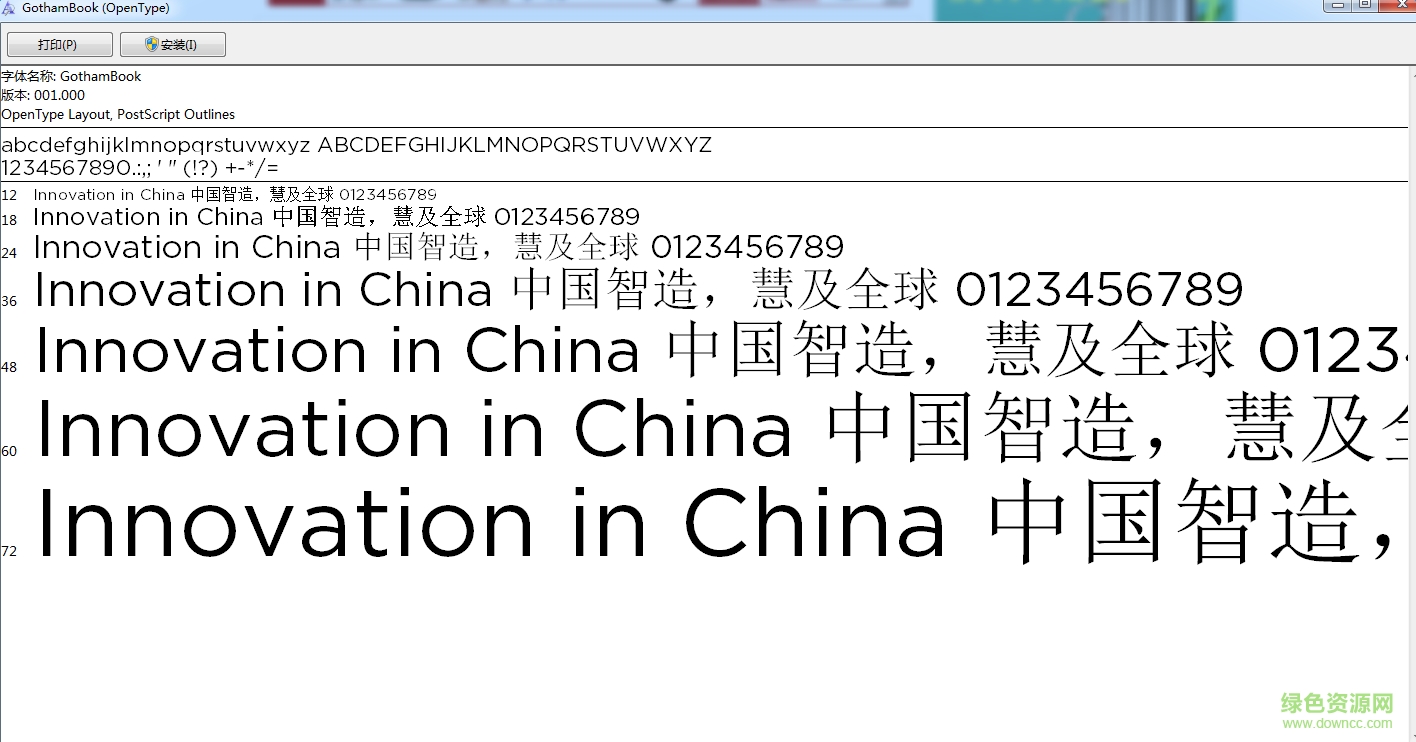
gotham book字體是一款制作精細(xì)的無(wú)襯線字體,結(jié)構(gòu)方正,規(guī)整劃一,現(xiàn)代感十足,可用于雜志、報(bào)刊的正文字體,也可用作廣告用字!
San Serif(無(wú)飾線),一種字母末端沒(méi)有短線裝飾線的字體。也被稱為grotesque(荒唐的),lineal(線性的)或者gothic(野蠻的,哥特的)。典型的非飾線字樣沒(méi)有開(kāi)始或者結(jié)束的筆畫(huà),所有起承轉(zhuǎn)合的筆畫(huà),看起來(lái)也都是一樣粗細(xì)的。